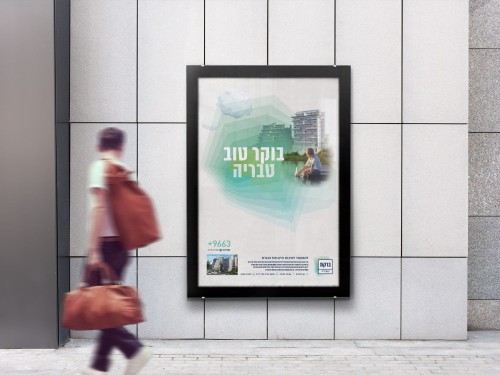
על אודות פונט אלמוני צר
אלמוני צר הוא פונט סנס מולטי־לשוני יסודי ומוקפד שבעשור האחרון הפך לאחד הפונטים הפופלאריים בישראל ולקלאסיקה תרבותית. הגרסה הנוכחית (גרסה 5) כוללת 1,151 תווים ותמיכה מלאה בעברית, אנגלית, רוסית ועוד 230 שפות לטיניות וקיריליות. בעבר הפונט נקרא ״אלמוני דו־לשוני״ ו״אלמוני חדש״. בעוד פונטים רבים מאופיינים בשפה ובאופי ייחודיים להם, אלמוני משיל מעצמו כמעט כל אלמנט של ייחוד. ככזה הוא לא ישתלט על העיצוב שתרקחו בעזרתו והוא ישמש אתכם בנאמנות למשך שנים רבות.. הפונט גם כולל משקל דקיק לכותרות ענק שאינו כלול במשפחה וניתן לרכישה בנפרד (דברו איתנו).
המלצת שימוש לפי משקל
אולטרה־לייט לכותרות גדולות 72 pt/px ומעלה
לייט, רגיל, בינוני, דמי־בולד ובולד לכותרות 24 pt/px ומעלה
דמי־בולד, בולד ואולטרה־בולד ללוגואים ולכותרות
✱ בתור כלל אצבע פונטים צרים מיועדים לכותרות. לטקסט־רץ השתמשו בפונט אלמוני חדש -
OpenType Features
- Small capitals אבג 123 Abc ← אבג 123 Abc
- ליגטורות סטנדרטיות office ← office
- ליגטורות סודיות History ← History
- אשכרה ← אשכרה
- ניקוד מדוקדק קֳשּׁ ← קֳשּׁ
- פיצ׳ר מגדרי דרושים/ות ← דרושים/ות
- א. ה ת י יו םן
- מספרים סִדּוּרִיים May 21st ← May 21st
- שברים, מוֹנֶה וְמְכַנֶּה 3/4 ← 3/4
- חלופות הקשריות גברת ← גברת
- חלופות סגנוניות a ← a
- אותיות מקוצרות לכותרות קלף ← קלף
- ₪ בגבהים שונים ₪ ₪ ₪ ₪